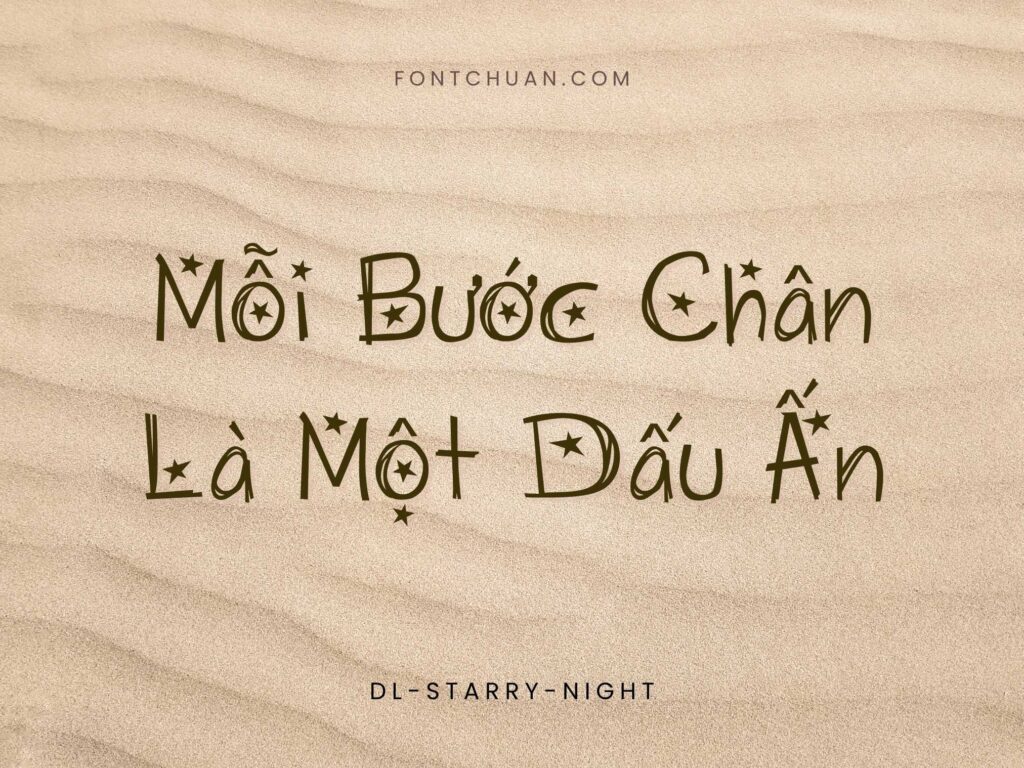
Font DL Starry Night Việt Hóa
Tác giả Font: Lauren Ashpole
Starry Night là một font chữ viết tay độc đáo, mang lại cảm giác tự nhiên và thân thiện cho các thiết kế. Được tạo ra bởi Brittney Murphy, font này kết hợp giữa sự đơn giản và nét duyên dáng, phù hợp cho nhiều mục đích sử dụng khác nhau. Với sự Việt hóa của Tduy, Starry Night hỗ trợ đầy đủ các ký tự tiếng Việt, giúp người dùng dễ dàng áp dụng trong các dự án thiết kế đa ngôn ngữ. Thành viên của Font Chuẩn đã sưu tầm và chia sẻ font này để đáp ứng nhu cầu của cộng đồng thiết kế.
Về đặc điểm thiết kế, Starry Night sở hữu các nét chữ mềm mại, uyển chuyển, tạo nên sự ấm áp và gần gũi. Font bao gồm đầy đủ chữ hoa, chữ thường, số và các ký tự đặc biệt, mang lại sự linh hoạt cho người thiết kế. Starry Night đặc biệt phù hợp cho các dự án như thiệp mời, poster, bao bì sản phẩm, thiết kế logo và các ấn phẩm quảng cáo. Ngoài ra, font này cũng thích hợp cho các sự kiện như lễ hội, sinh nhật, Valentine và Trung thu, mang lại không khí vui tươi và ấm áp. Trong lĩnh vực ngành nghề, Starry Night được ứng dụng rộng rãi trong quảng cáo, thiết kế đồ họa, giáo dục và công nghệ, góp phần tạo nên sự độc đáo và thu hút cho các sản phẩm và thương hiệu.